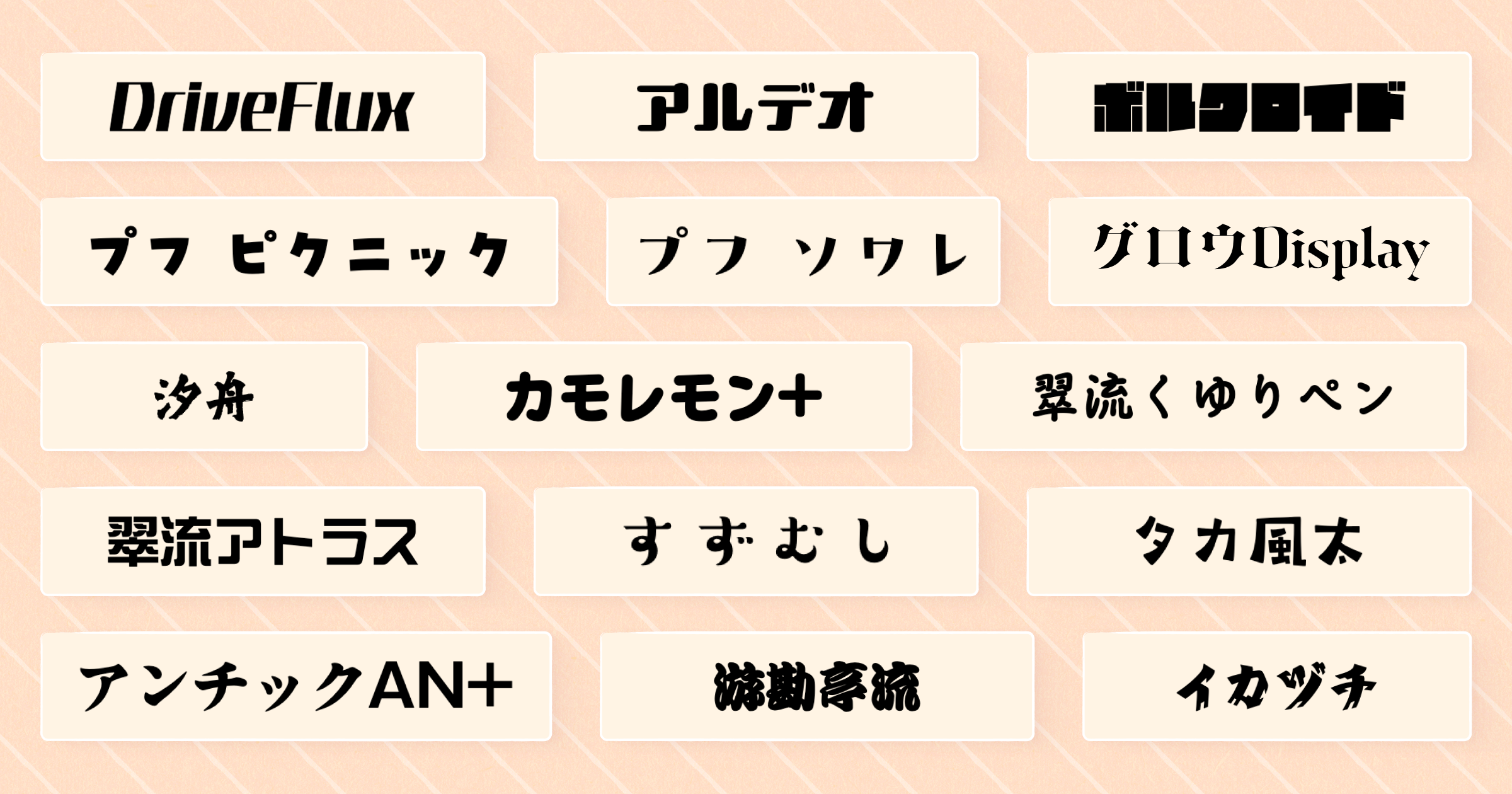
オリジナルグッズ作成サービス「pixivFACTORY」にモリサワフォントの提供を開始!採用を記念してフォントの日(4/10)よりInstagramキャンペーンを実施
株式会社モリサワ(代表取締役社長:森澤彰彦 本社:大阪市浪速区、以下モリサワ)は、ピクシブ株式会社(代表取締役CEO:丹羽康弘 本社:東京都渋谷区)が運営するオリジナルグッズ作成サービス「pixivFACTORY(ピクシブファクトリー)」にフォントの提供を開始しました。
今回の提供により、「pixivFACTORY」のユーザーは、グッズ制作に欠かせないテキスト入力機能にモリサワのフォントを使用することができます。
提供するフォントは、力強さやスピード感を細部まで表現できるバリアブルフォント「DriveFlux(ドライブフラックス)」から厳選した7スタイルに加え、「プフ ピクニック」など人気の高いデザイン書体を中心とした計15書体です。個性的なフォントが、オリジナルグッズをより魅力的に演出します。
提供書体
アルデオ
アンチックAN+
イカヅチ
カモレモン+
グロウDisplay
汐舟
翠流アトラス
翠流くゆりペン
すずむし
タカ風太
プフ ソワレ
プフ ピクニック
DriveFlux(※)
ボルクロイド
游勘亭流
※あらかじめ各軸の値が設定された7スタイルをご用意しています。
今回は「pixivFACTORY」に提供したフォントを使って、同サービス内のアクリルお守りをオリジナルデザインで制作しました。お守りは、制作に携わる方にとって縁起の良い「ひらめき御守」、組版や文字にまつわるデザインにちなんだ「組版上達御守」など、制作安泰の願いを込めた全5種類です。お守りに記された言葉は当社が遊び心で創作したもので、それぞれの言葉に合うフォントを選んでデザインしました。ぜひ身につけていただき、日々の制作を見守るお守りとしてお楽しみください。
誤植退散御守(イカヅチ)
※()内は使用書体名